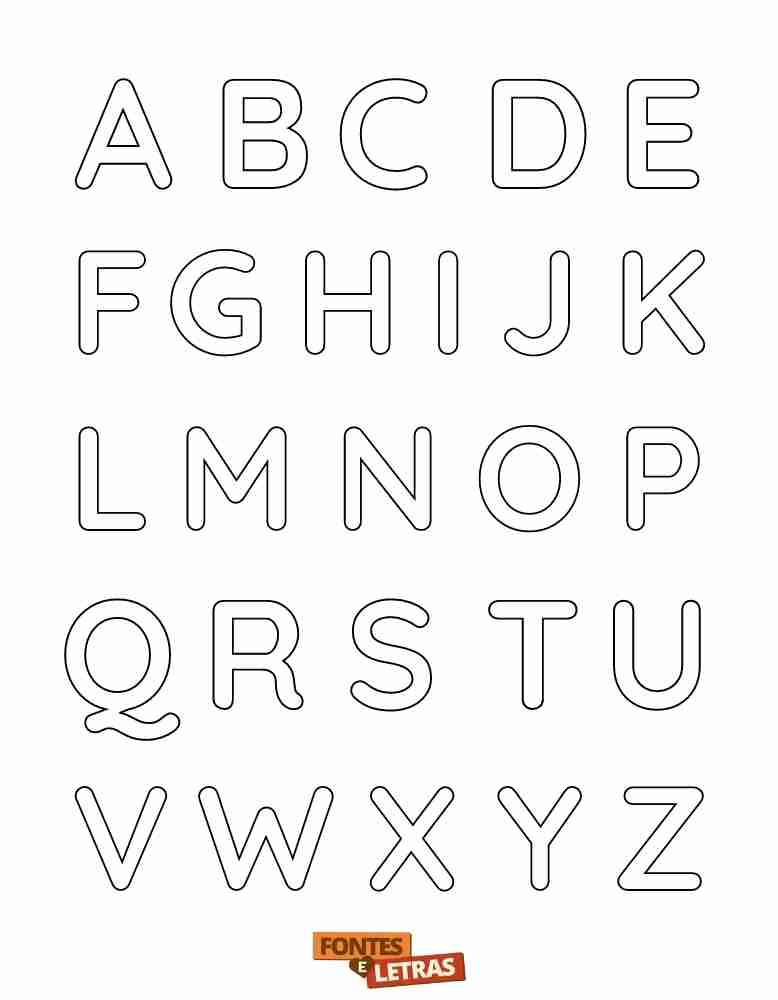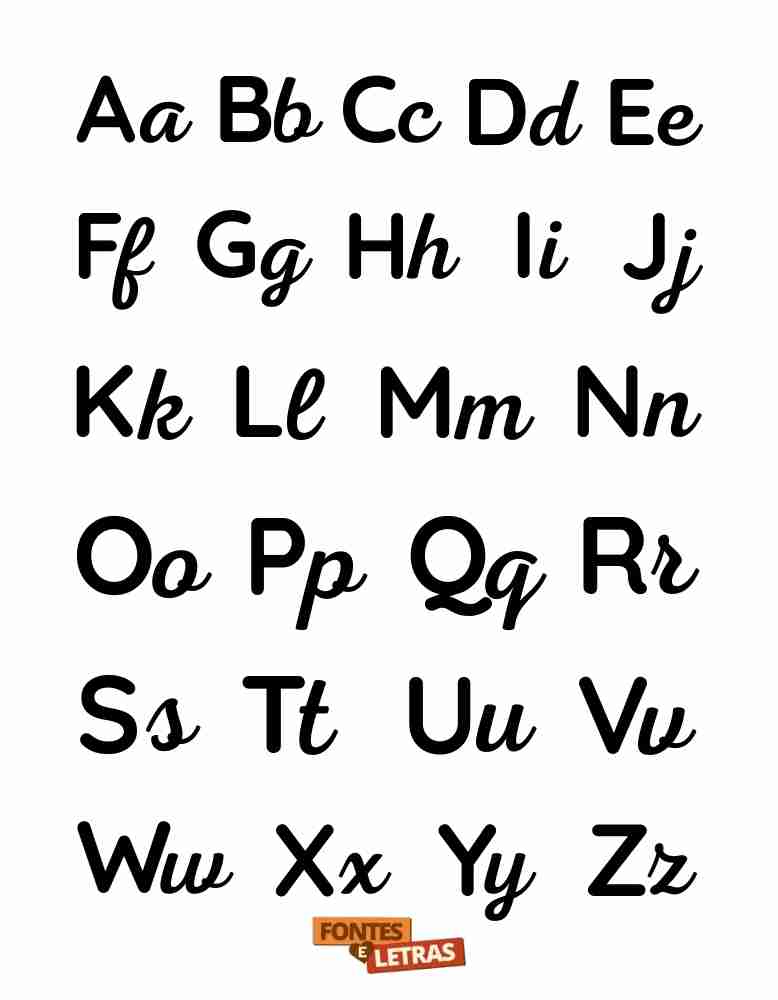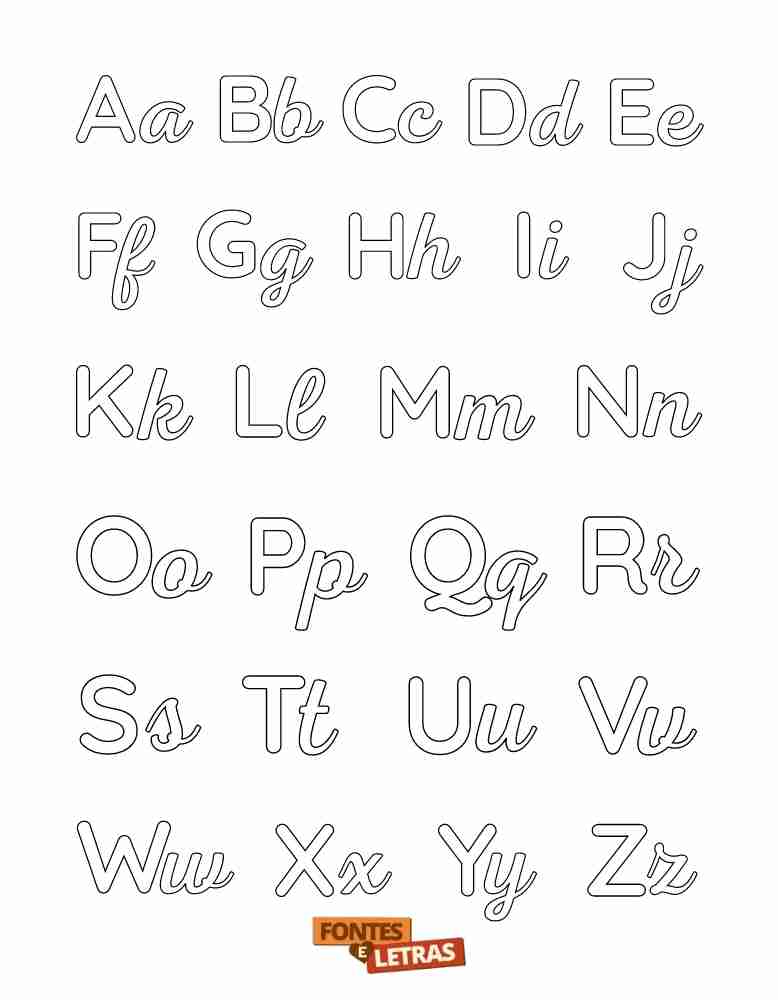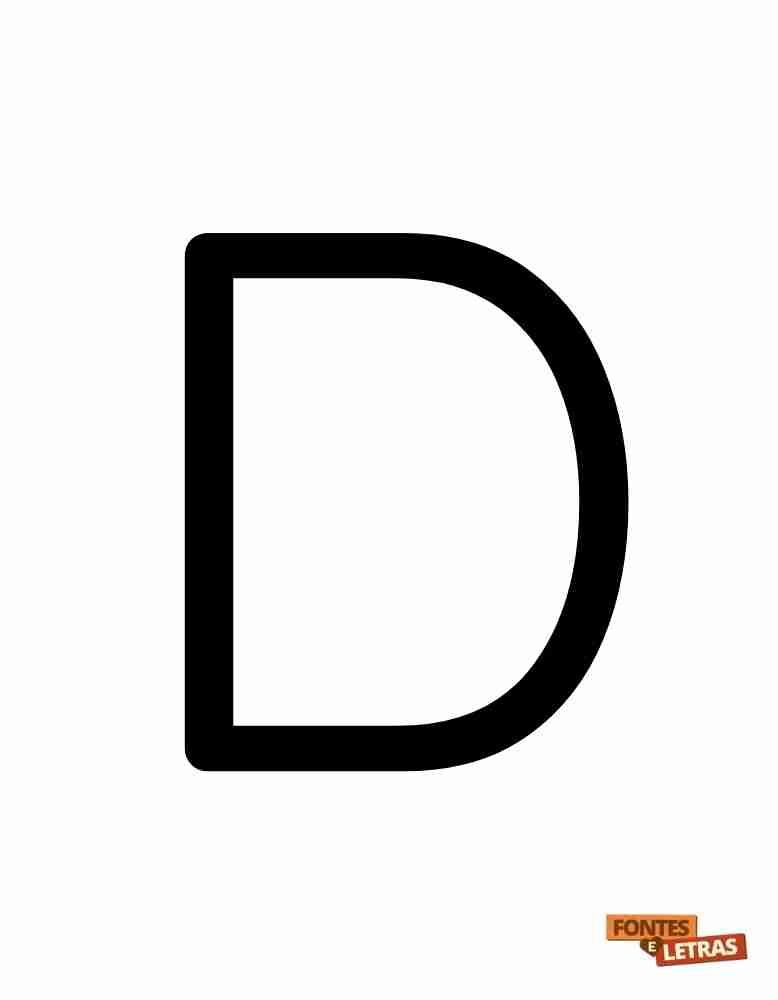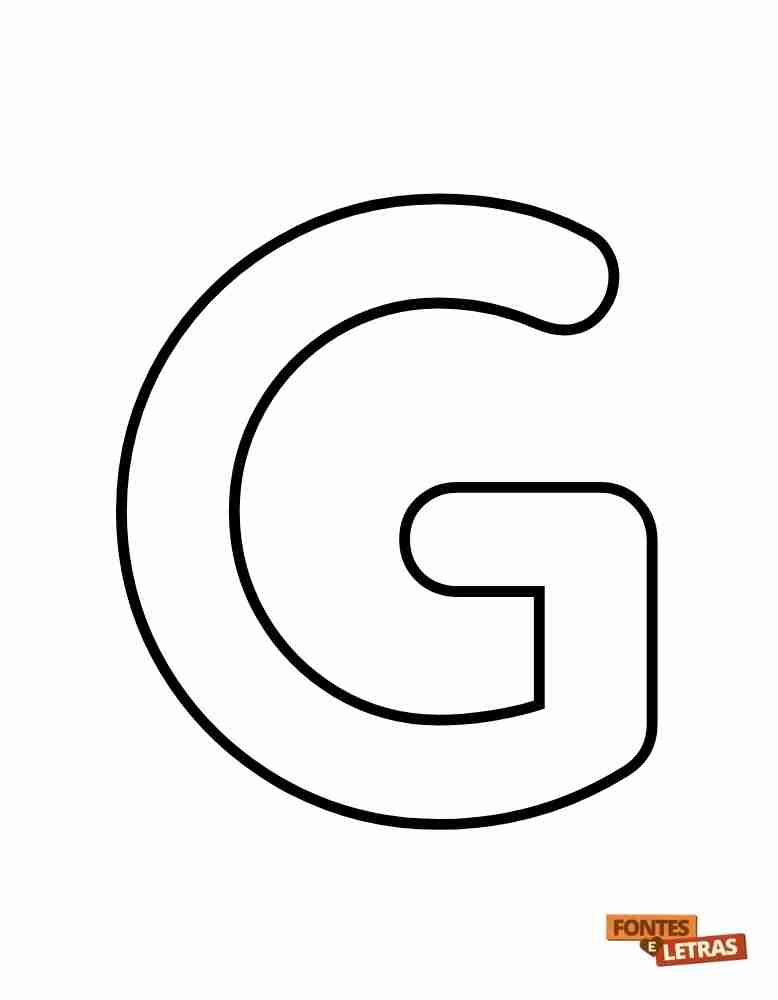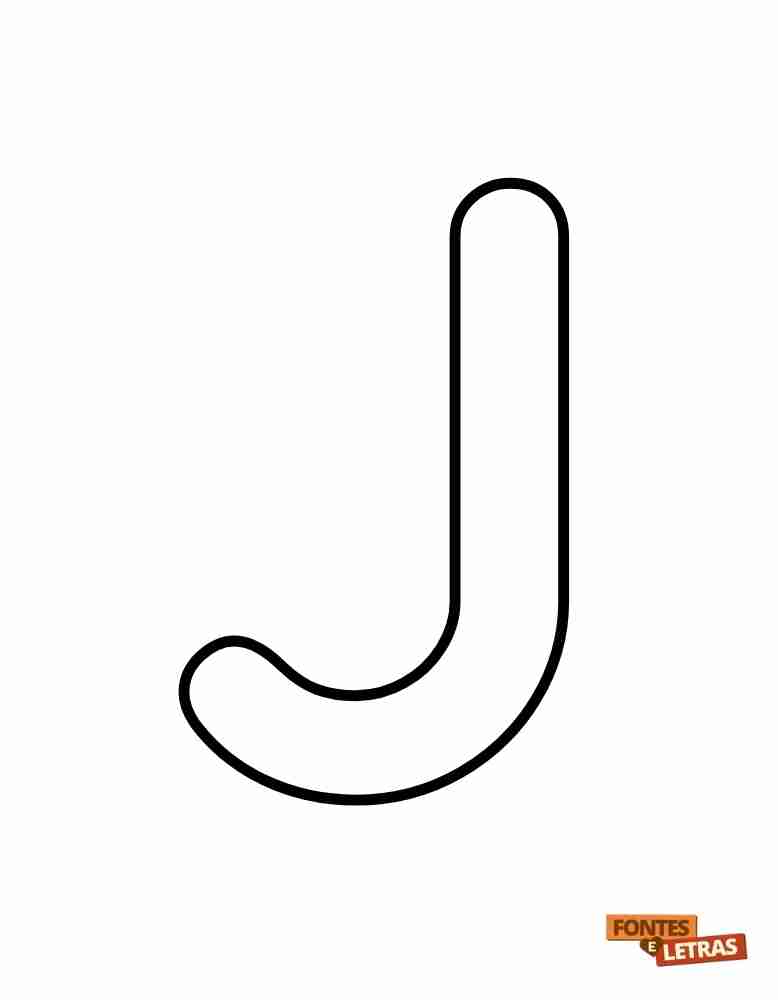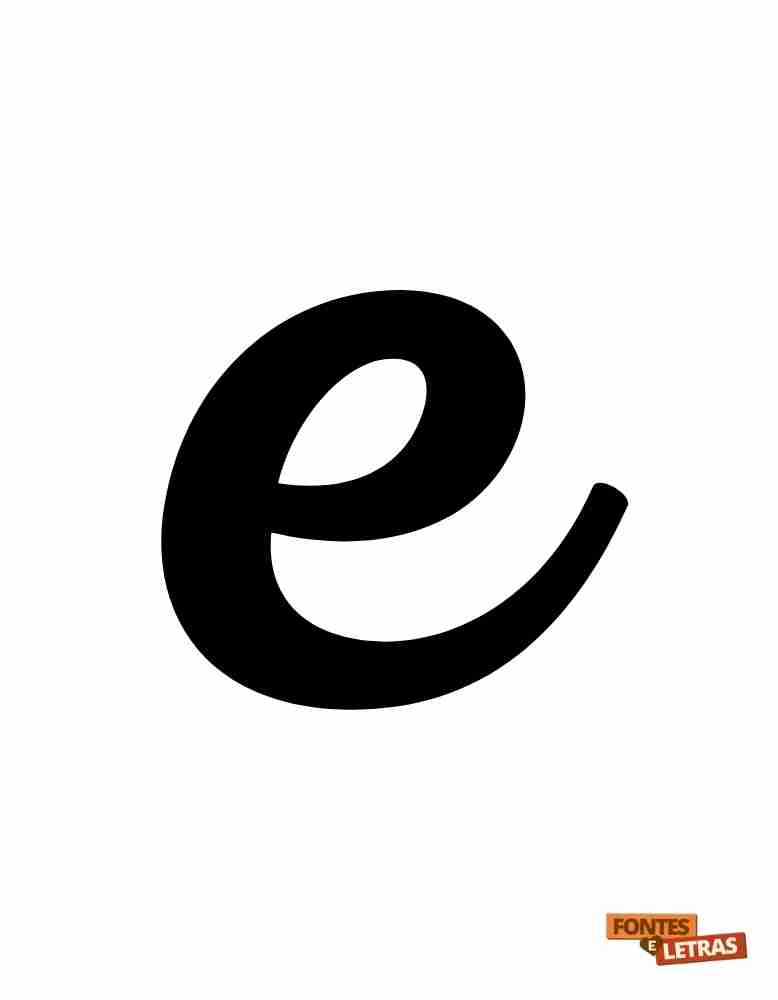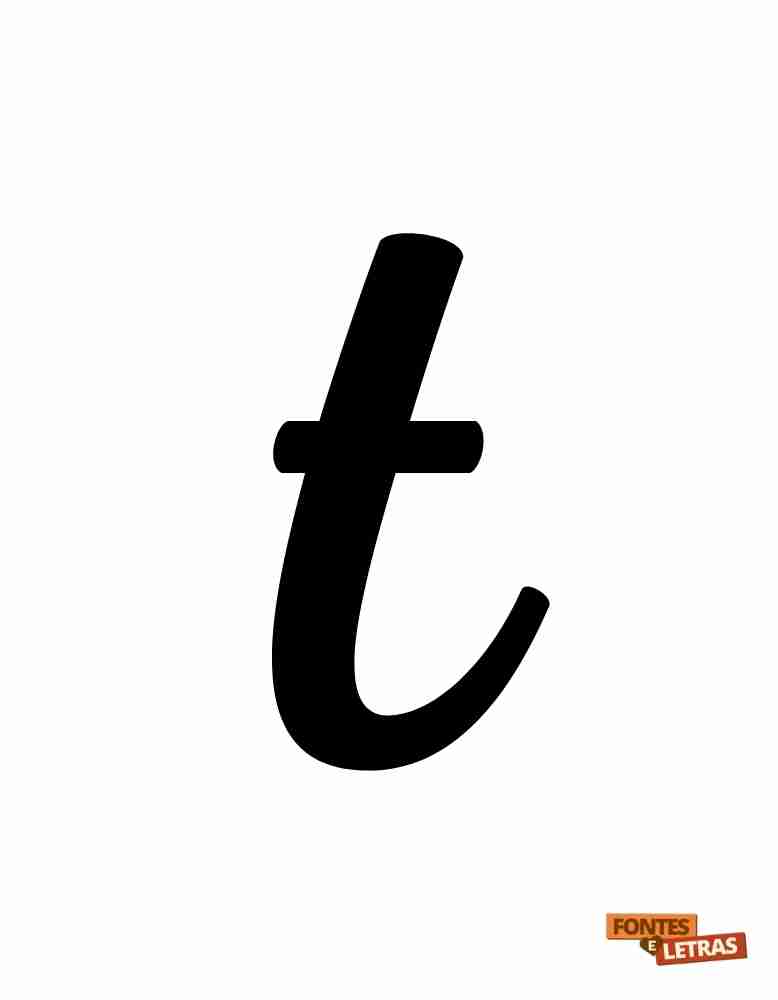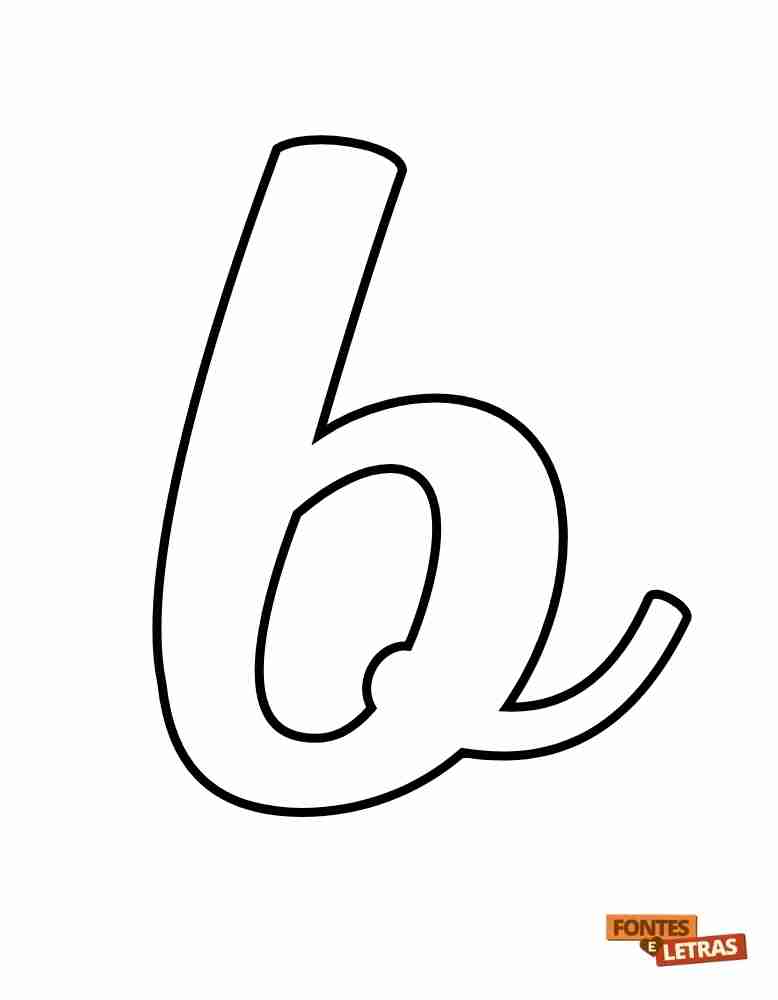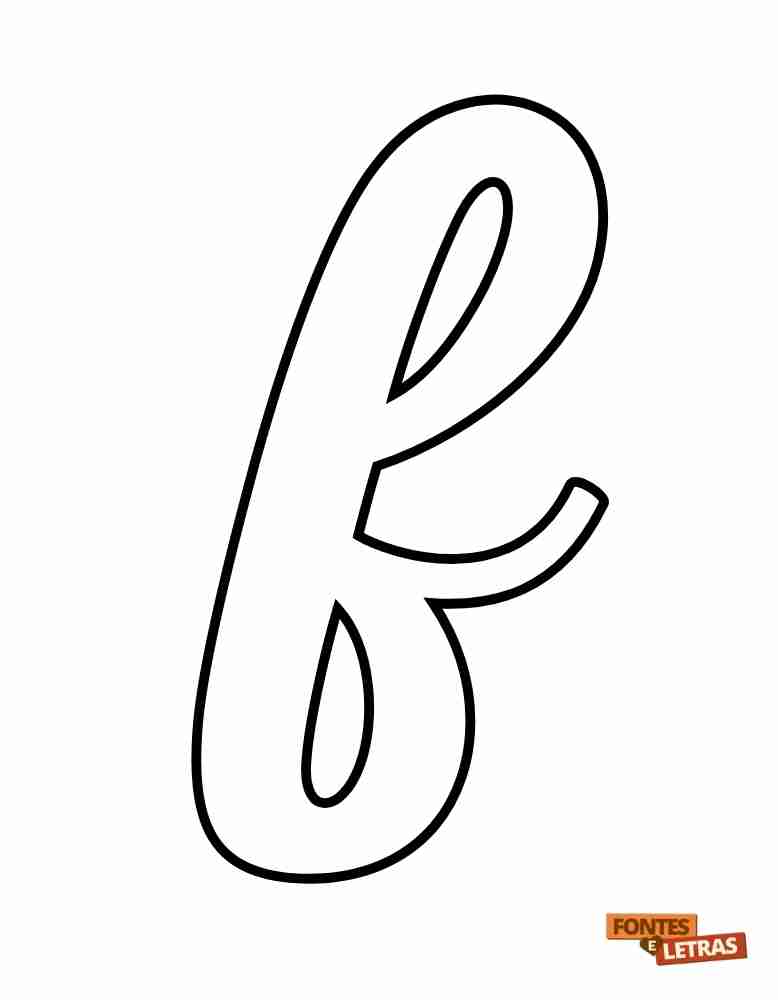
Fontes e Letras grandes para imprimir, colorir e pôsteres
O uso de letras grandes ou de letras para colorir é muito popular, especialmente quando se tem crianças pequenas, pois funciona muito bem para revisar o que elas aprenderam e para entendê-lo melhor.
A partir dos 3-5 anos de idade, as crianças adquirem a capacidade de identificar algumas das letras do alfabeto e uma ótima maneira de incentivar esse aprendizado é usar letras grandes para decorar ou imprimir.
À medida que o processo avança, outras atividades podem ser realizadas, que não são úteis apenas para crianças.
Livros de alfabeto e folhas para colorir
Letras grandes para imprimir
# Padrão maiúsculas
# Padrão maiúsculas para colorir
# Padrão minúsculas
# Padrão minúsculas para colorir
# Padrão minúsculas e maiúsculas
# Padrão minúsculas e maiúsculas para colorir
# Padrão minúsculas e maiúsculas com palavras e imagens
# Padrão minúsculas e maiúsculas para colorir e brincar com palavras
# Padrão para praticar a pancada
Melhores fontes para alfabetos e moldes
Na realidade, não há limites quando se trata de fontes ou letras para colorir. Os conversores de letras e fontes oferecem milhares de opções para que você possa sempre encontrar a que melhor se adapta ao que está procurando ou ao que deseja.
Recomendamos apenas que, dependendo do tipo de atividade que deseja realizar, você opte por tipografias que possa entender para que não haja confusão no aprendizado e o processo seja ágil.
Dicas para selecionar letras para impressão
Se você já sabe para que vai usar as cartas, concentre-se no que precisa e escolha as que oferecem a possibilidade de explorar a atividade que deseja fazer.
Por exemplo, se você quiser letras bonitas para decorar, concentre-se em fontes mais grossas para que haja espaço para elas colorirem, e isso não é uma limitação. As opções são amplas, portanto, você não terá problemas em sua pesquisa.
Se você não tiver um plano claro, a melhor coisa a fazer é examinar várias opções para se inspirar e, com base no que encontrar, decidir o que fazer, ou seja, obter novas ideias.
Qual é a finalidade da impressão em letras grandes?
Os moldes para impressão em tamanho grande são úteis para uma ampla gama de atividades, como, por exemplo, fazer pôsteres, estimular o aprendizado de crianças pequenas, entre muitas outras coisas.
Você pode imprimir as letras para colorir, preenchê-las com diferentes elementos, como bolas de papel, para tornar a dinâmica mais divertida e incentivar o aprendizado sem que ele ocorra de forma 100% consciente.
A realização desse tipo de atividade não apenas ajuda as crianças a aprender a ler, mas também permite que elas desenvolvam suas habilidades psicomotoras, tornando-as mais animadas e ágeis.
Processo para imprimir as cartas e usá-las
Tudo o que você precisa fazer para começar a usar as letras grandes para seus diferentes objetivos é o seguinte:
- Veja as opções nesta página de cima para baixo.
- Clique na fonte de sua escolha e o alfabeto completo será exibido automaticamente.
- Um PDF será aberto com as fontes escolhidas. Clique com o botão direito do mouse e clique em salvar (ou no botão salvar mostrado na tela).
Agora você pode fazer as atividades que quiser com os moldes de letras que obteve. Um dos usos mais comuns é para aprender o alfabeto, portanto, você pode começar por aí se tiver um filho pequeno.